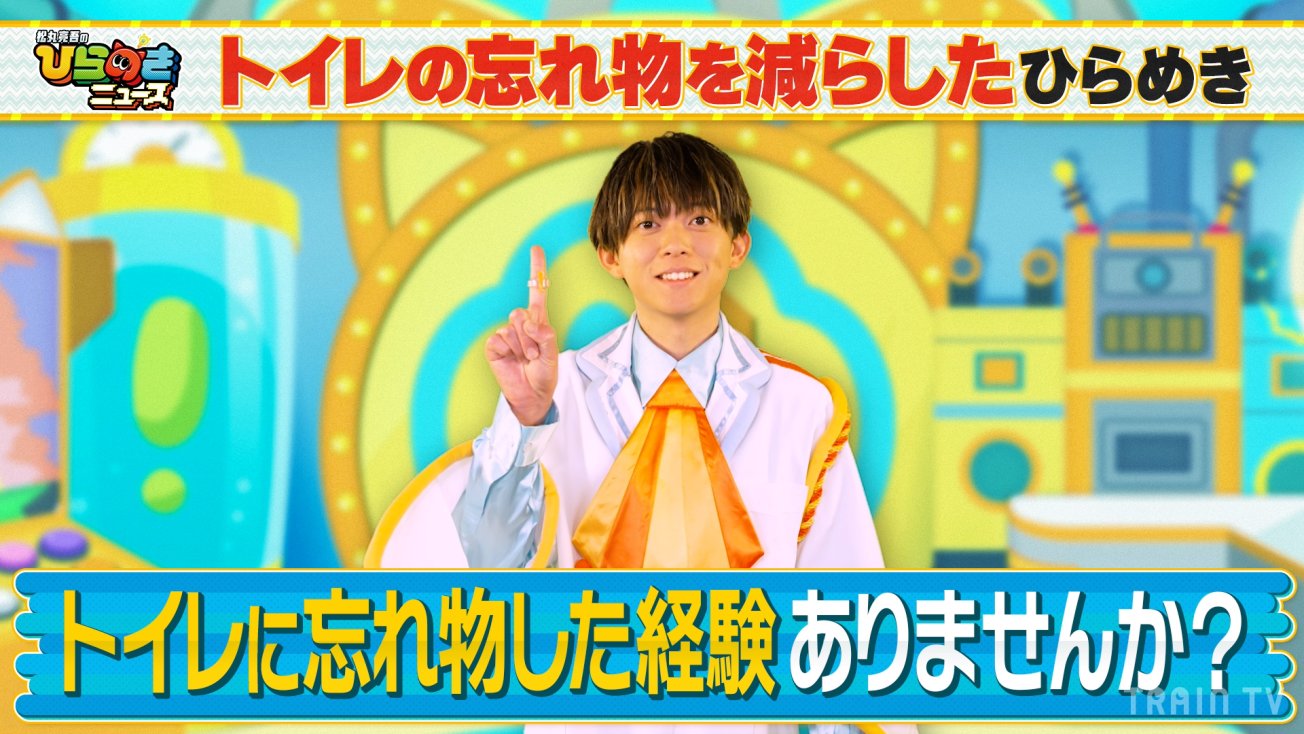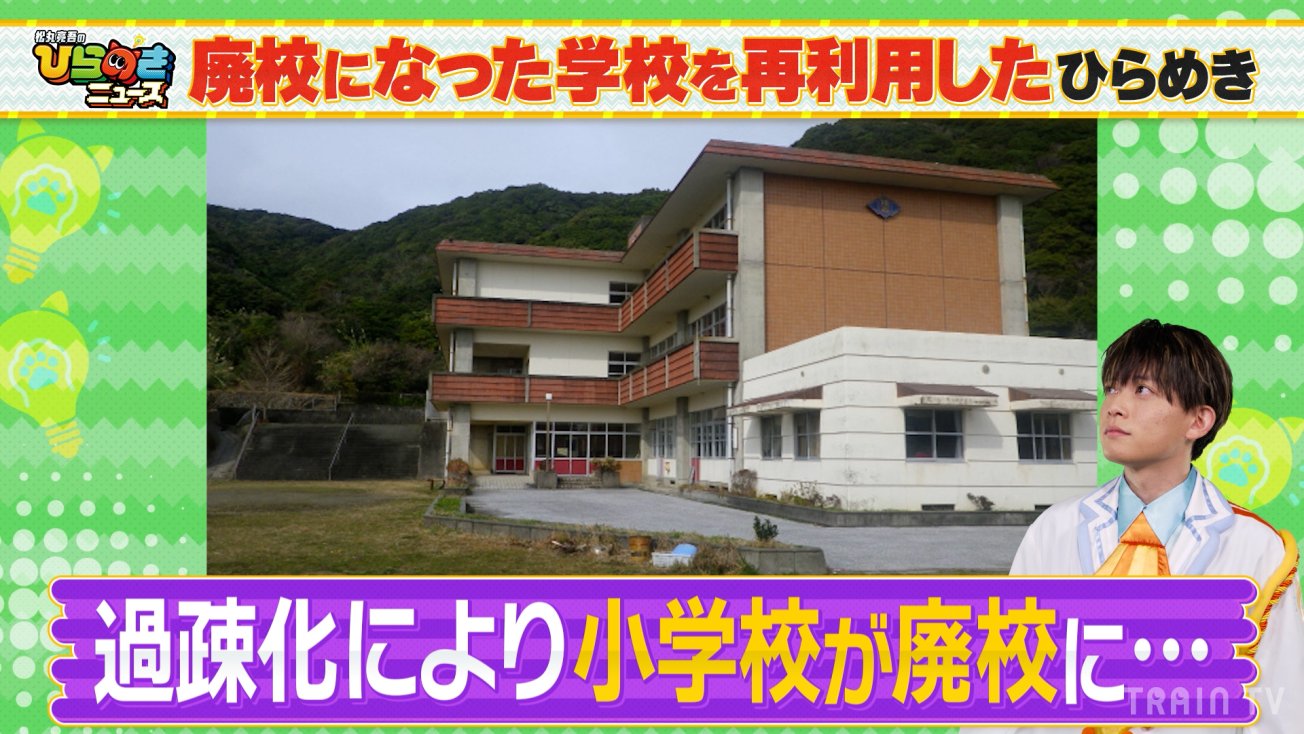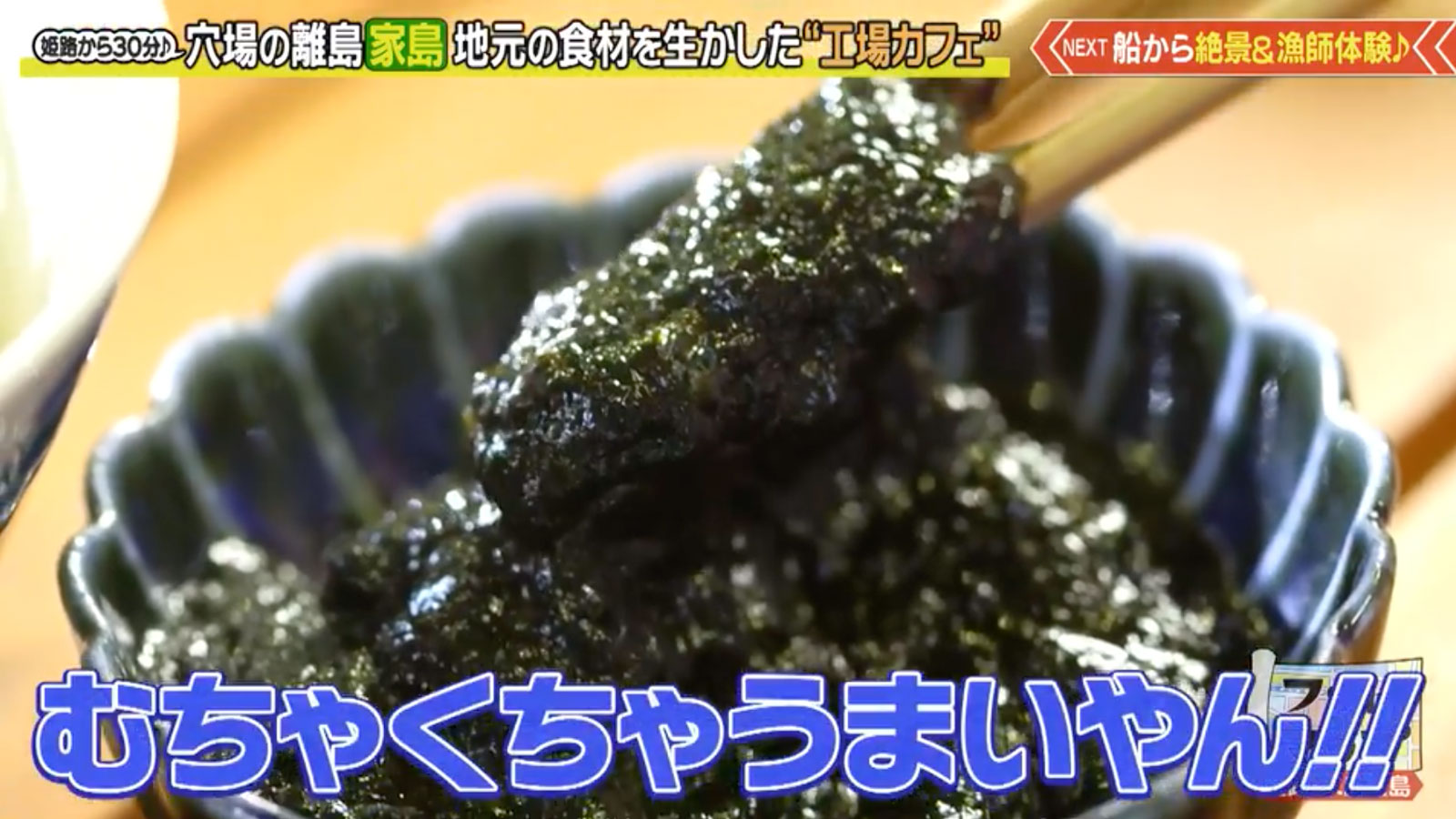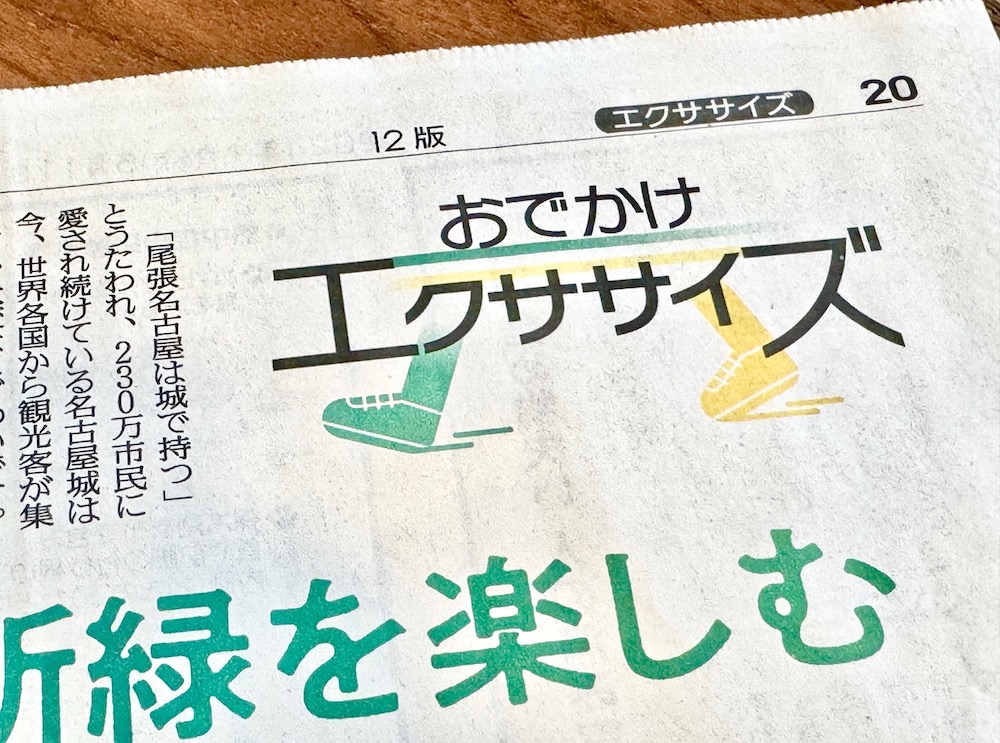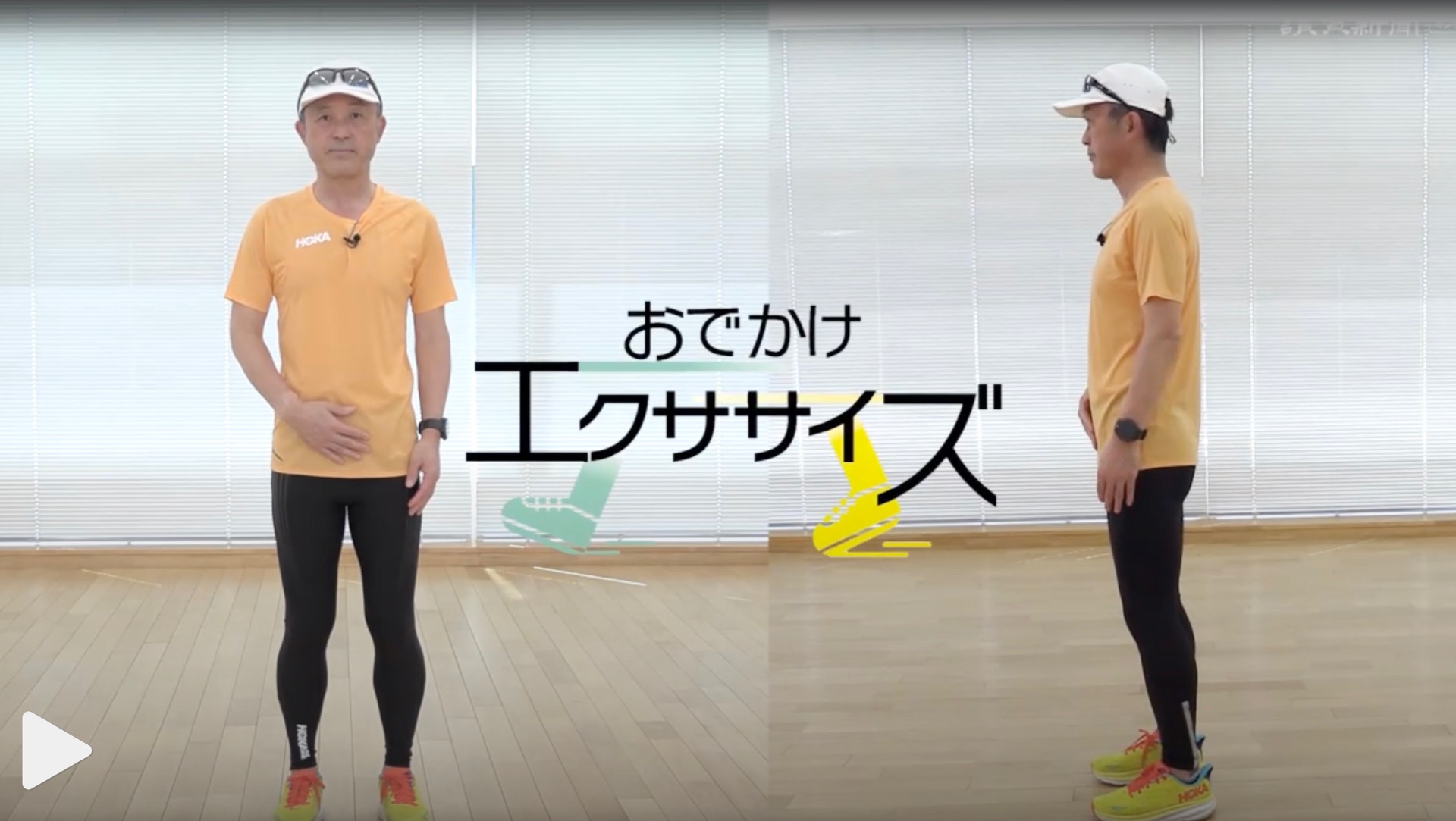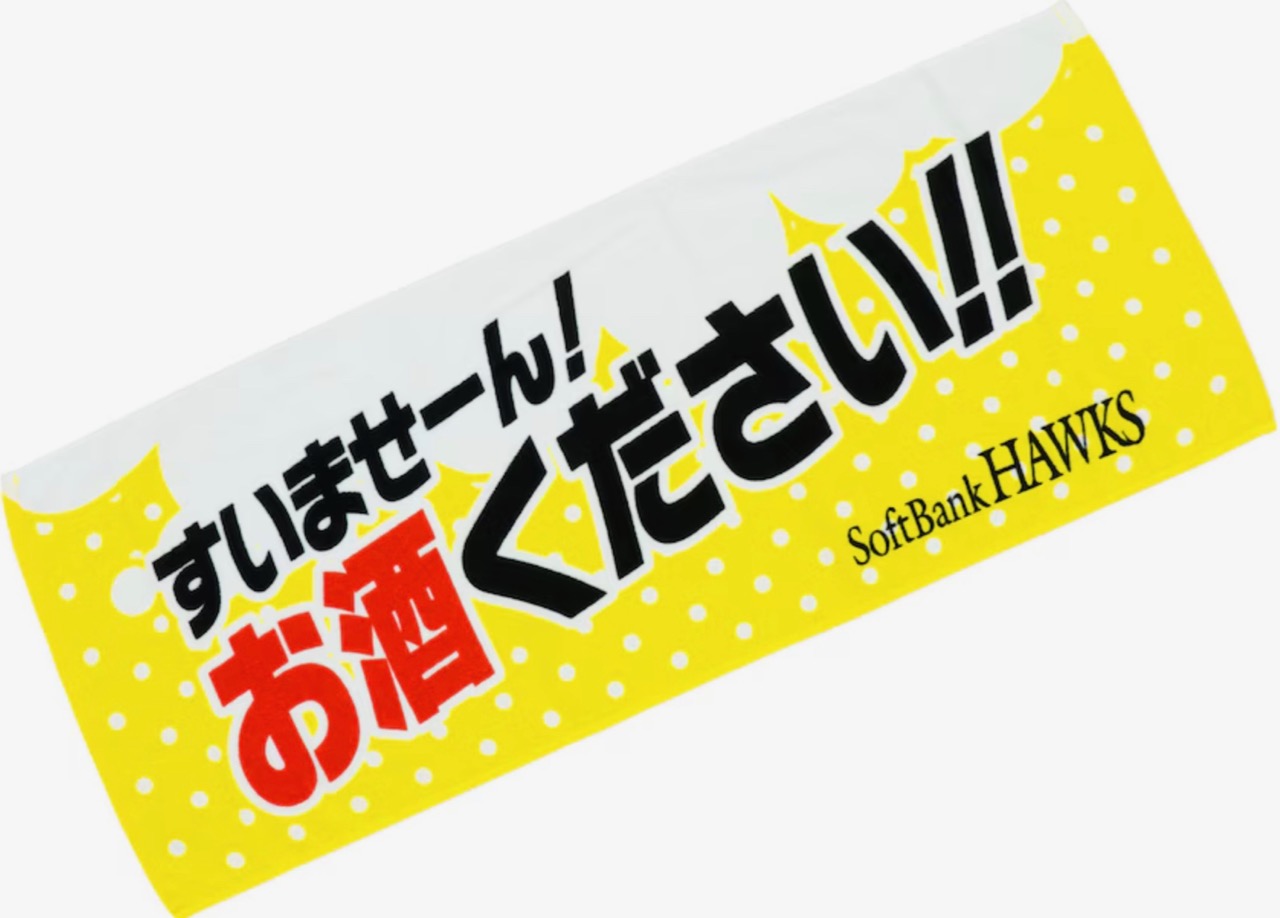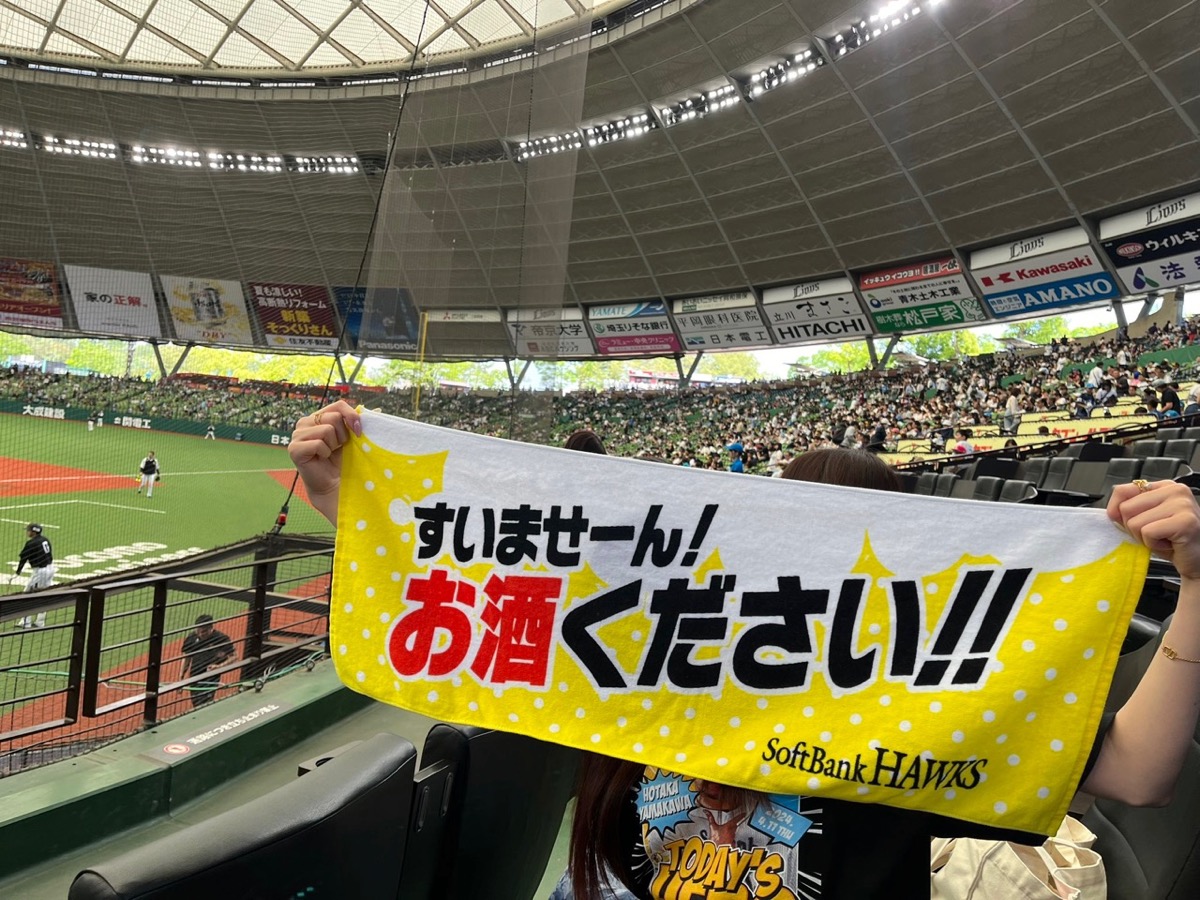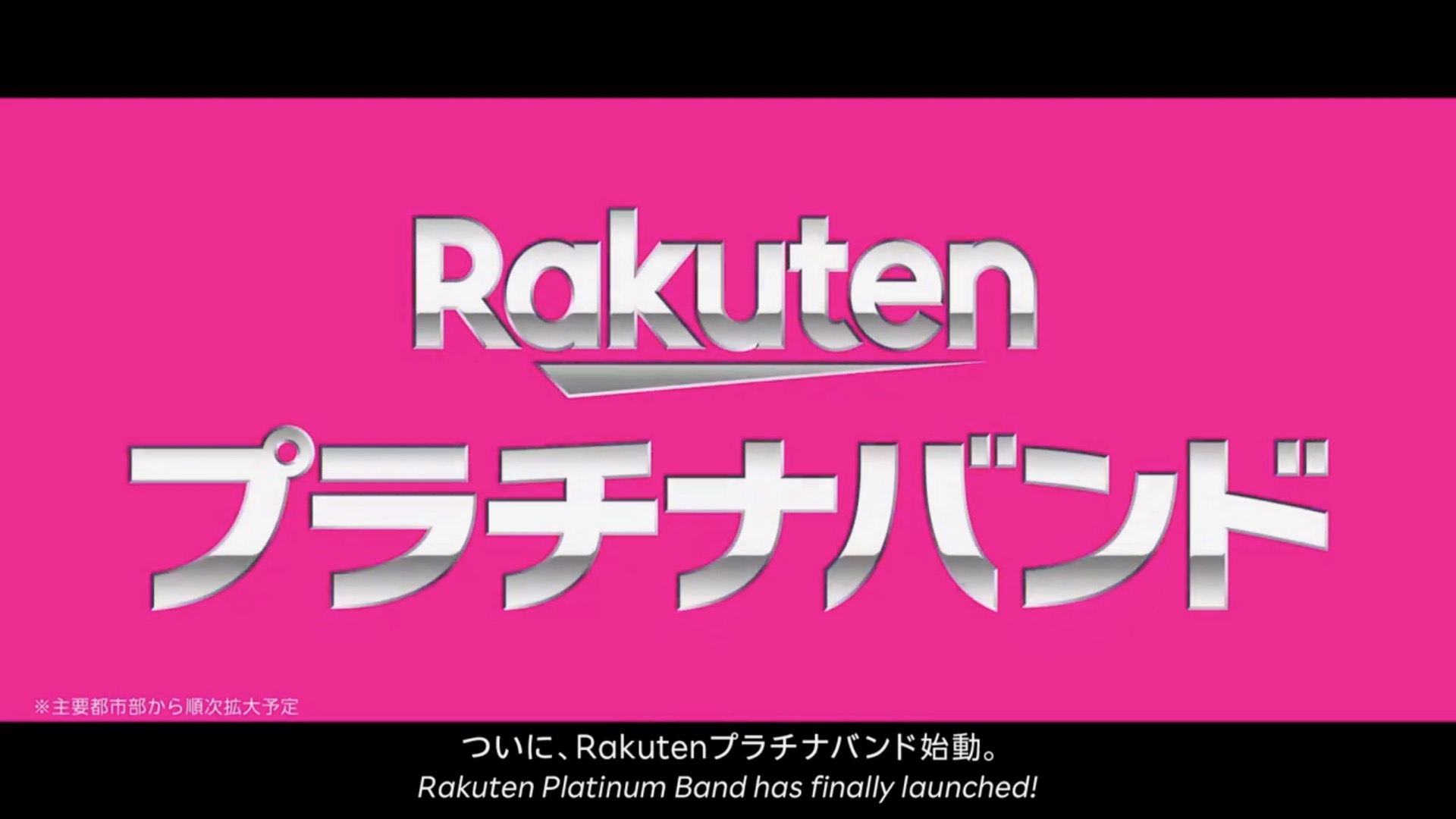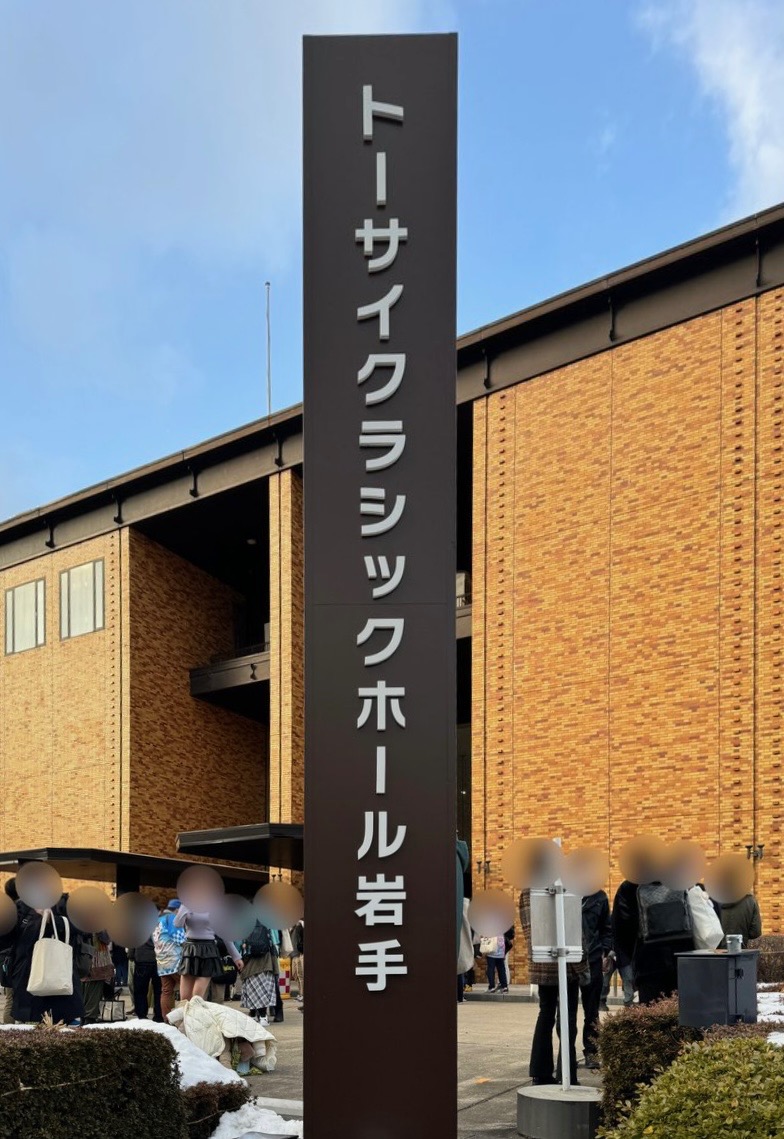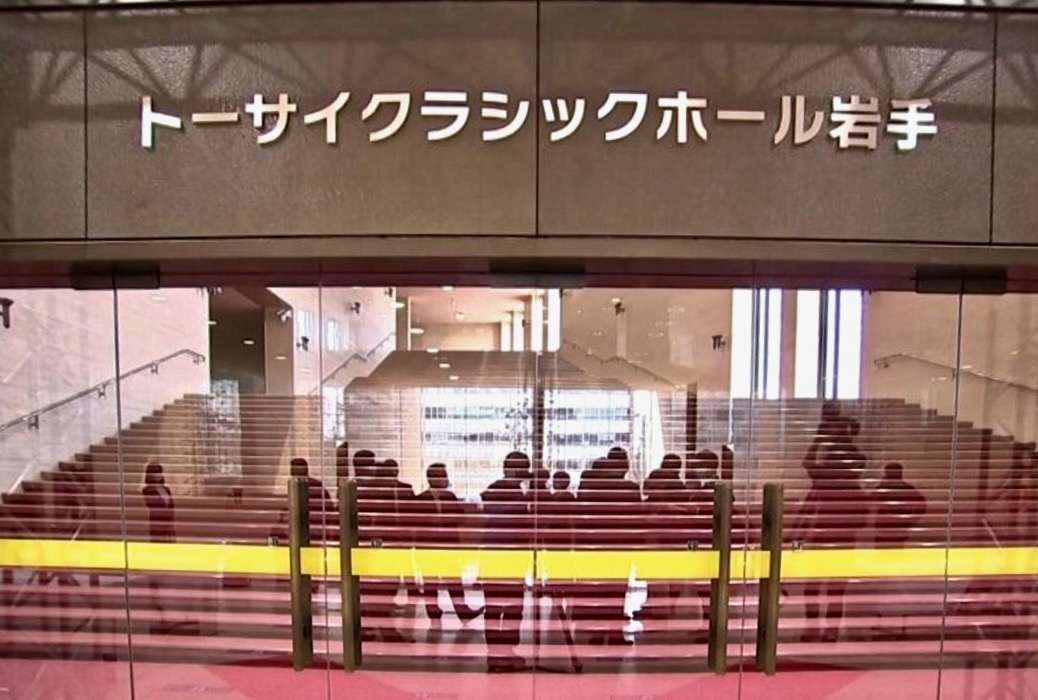
ケンミンショーで  さとうゆたか  2026年4月23日(木) 9:08
この書体、テレビ放送業界では大人気です。
こういう風に、たくさん使われている。
一番くじ倶楽部。
これも、このサイト内で。
これもだね。
若干変わった「めざましテレビ」のニタラゴ  takumi  2026年3月30日(月) 9:48
めざましテレビで2013年春頃から採用されているニタラゴ。
長年使われていたのは「ロダンNTLG」でしたが、今日辺りから「タイプラボN+」(新ゴと混植済みのフォント)に変更されたようです。
毎朝「めざましテレビ」を見てます。
ロダンより新ゴの方が、漢字の大きさにムラがなくて整って見えますね…。
MOOKの表紙  さとうゆたか  2026年3月25日(水) 16:05
書名:はじめてのクルーズ パーフェクト・ガイドブック
発行:海事プレス社
同じシリーズかな。
バスのロゴマーク  みきお  2026年3月9日(月) 22:26
京成バスの事業者別ロゴマークに、ニタラゴルイカが使用されていました。左の画像は同社路線バス内の採用募集広告の一部です。「京成」グリフの一部は、グラフィックソフトで描き起こしたものと思います。
同社採用ページにも使用されています。
広告画像  さとうゆたか  2026年3月5日(木) 10:19
マクドナルドの広告では、長いあいだ使われている。
もうひとつ。
本の表紙  さとうゆたか  2026年2月22日(日) 10:12
書名:ポケモン サイエンスブック でんき
著者:岩崎 孝之(監修)
発行:小学館
広告画像  さとうゆたか  2026年2月7日(土) 9:07
ユニクロと「地球の歩き方」がタイアップしてるようだ。
ポケモンみっけ!  さとうゆたか  2025年12月31日(水) 10:42
セブン-イレブンのポケモンキャンペーン!
実際の商品パッケージ。
絵本の表紙  さとうゆたか  2025年12月12日(金) 10:27
書名:のぞいてみようクリスマス
著者:アナ・ミルボーン、エマ・アレン(絵)、青木(訳)
発行:大日本絵画